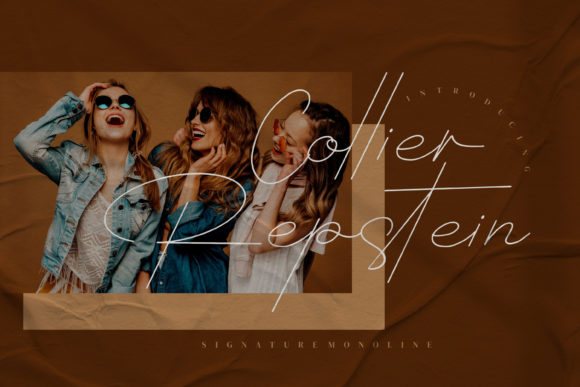
Creativefabrica Collier Repstein Font 2021
[Creativefabrica] Collier Repstein Font (2021)
Collier Repstein - прекрасный шрифт с тонким начертанием.
Он украсит широкий спектр идей по созданию открыток, брендинга, этикеток и многого другого.